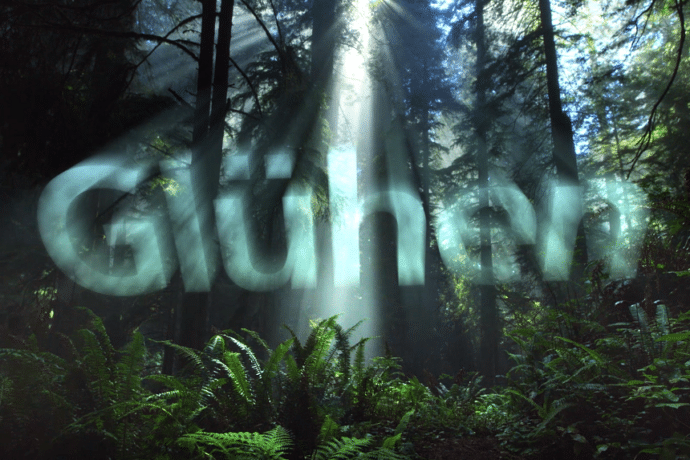
#MeetSST: Der Font- und Technologie-Anbieter Monotype hat die SST® Schriftfamilie veröffentlicht, eine zeitlose Sans-Serif für Marken und Unternehmen, die auf internationalen Märkten und Kanälen aktiv sind. Entwickelt wurde sie in den Monotype Studios unter der künstlerischen Leitung von Akira Kobayashi. Die Unterstützung von fast 100 Sprachen sowie ihr klares Design und beste Lesbarkeit machen SST zu einer der vielseitigsten Schriftfamilien auf dem Markt. Mit sechs Strichstärken, den dazu passenden Kursiven, sowie drei Condensed-Schnitten und zwei Typewriter-Fonts deckt die Latin-Version der Sans-Serif alle Anforderungen der industriellen Werbe- und Unternehmenskommunikation ab.
SST ist ein Originalentwurf, der auf bewährte typografische Designtraditionen aufbaut. Gestalterisch verbindet die Familie die gute Lesbarkeit eines humanistischen Type-Designs mit dem neutralen Charakter statischer Groteskschriften. Das Ergebnis ist eine maximal lesbare und flexibel nutzbare Corporate-Schrift, die sich für den Einsatz in allen Industriezweigen eignet. Ihre Einsatzgebiete sind nahezu unbegrenzt, beginnend beim Smartphone-Screen über den klassischen Printbereich bis hin zu Beschilderungen und Informationssystemen. Und weil diese Disziplinen in allen unterstützten Sprachen bedient werden können, erweist sich SST als ein produktives, verlässliches Kommunikationstool.
„Für internationale Marken ist es eine der größten Herausforderungen, ihre visuelle Kommunikation in allen Märkten und Regionen harmonisch und unverwechselbar zu gestalten“, betont Akira Kobayashi, bei Monotype als Type-Direktor für den asiatischen Sprachraum verantwortlich. „SST erweist sich auf jedem Anwendungsgebiet als vielseitige und gut lesbare Schrift, weil sie eigens für das ungetrübte MarkenerlebnisBrand Experience, im Deutschen auch Markenerlebnis genannt, bezeichnet die Gesamtheit aller sinnlichen, emotionalen und kognitiven Eindrücke, die Menschen über die gesamte Customer Journey hinweg mit einer Marke sammeln. Der Begriff ist bewusst weit gefasst: Er umfasst nicht nur den physischen Kontakt in Räumen oder auf Veranstaltungen, sondern jeden analogen wie digitalen Berührungspunkt, das Auspacken eines Produkts als Packaging Experience, die…
Weiterlesen: Markenerlebnis über alle Grenzen hinweg entwickelt wurde, ohne sich selbst in den Vordergrund zu spielen. Unser Anspruch bei solchen Projekten ist stets, globale Lösungen zu schaffen, die Bestand haben und ihre Geschichten zurückhaltend erzählen.“
Die SST-Familie wurde gemeinsam mit dem Kreativdepartment der Sony Corporation für den weltweiten Einsatz entwickelt, wobei Kobayashi und sein Team bei jedem Schriftschnitt viel Sorgfalt auf die Balance von Stilmerkmalen und lokale Gepflogenheiten in der Kommunikation legten. Das Ergebnis ist ein harmonisches Schriftbild für alle Märkte, mit dessen Hilfe sich ein konsistentes Markenbild an allen Orten vermitteln lässt, an denen Verbraucher mit der Marke in Kontakt treten: im Marketing, am Point of Sale, auf Produkten, online, im Druck und in den digitalen Medien.